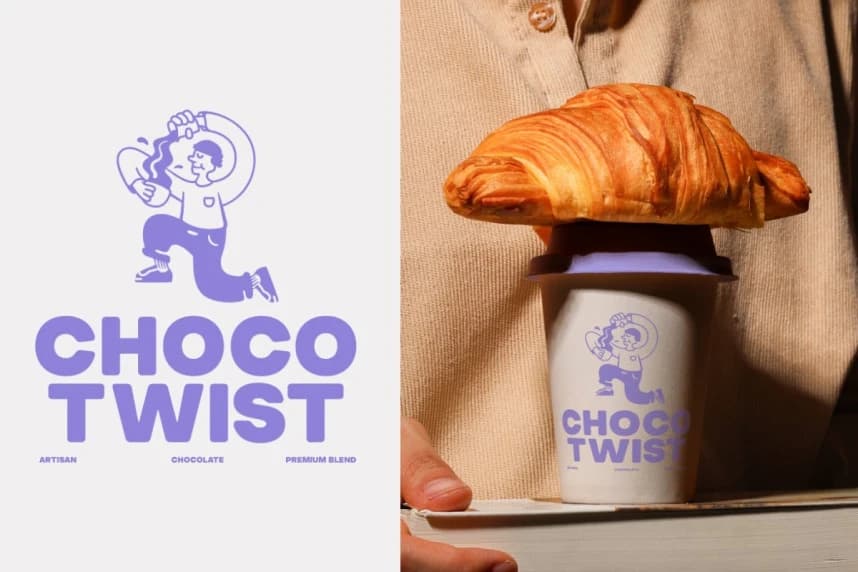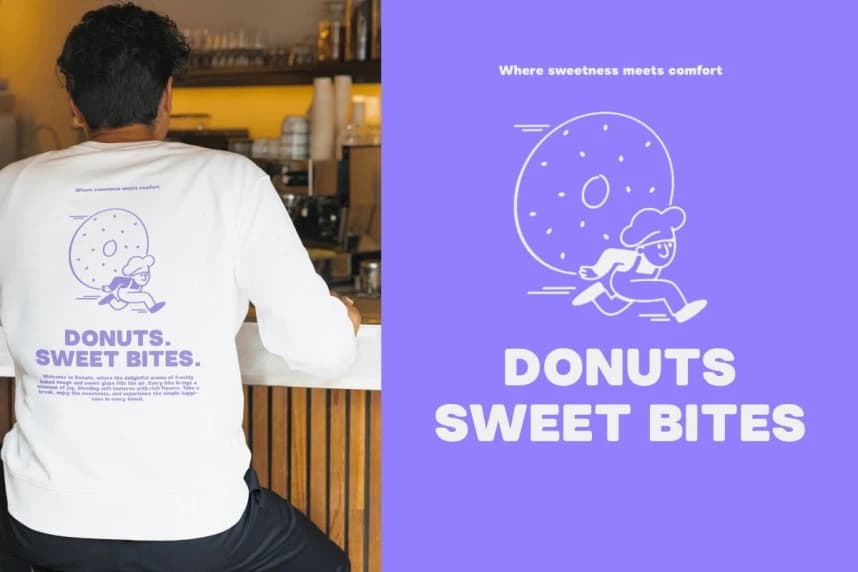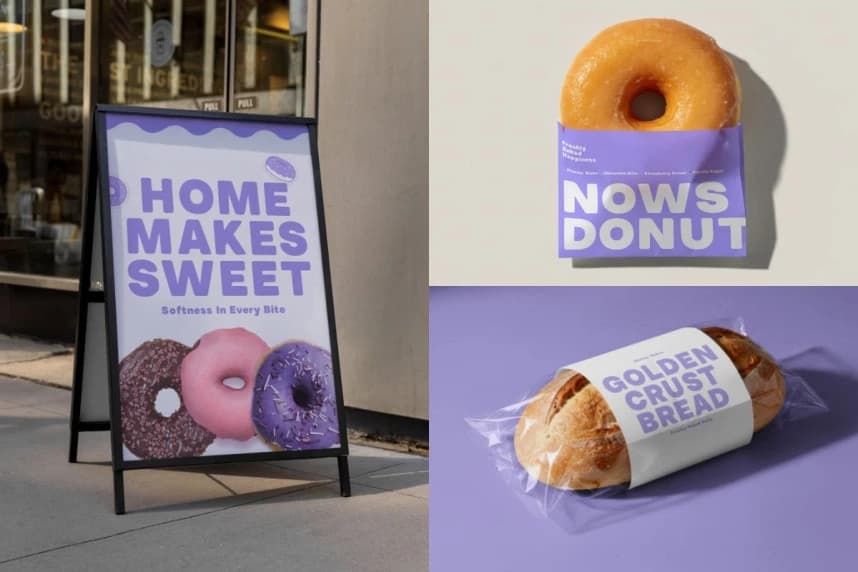
TBJ Moder Font
TBJ Moder Font, cesur ve modern bir görsel kimlik sunmayı amaçlayan çağdaş, yuvarlak hatlı bir gösteri yazı tipidir. Pürüzsüz eğriler ve temiz yuvarlak köşelerle tasarlanmıştır. Bu yazı tipi, büyük başlıklar ve modern markalaşmada öne çıkan dostça ama güçlü bir karakter sunar.
TBJ Moder Font, cesur ve modern bir görsel kimlik sunmak için tasarlanmış çağdaş, yuvarlak bir gösteri yazı tipidir. Akıcı eğriler ve temiz yuvarlak köşelerle üretilmiş olan bu yazı tipi, büyük başlıklar ve modern marka kimliğinde öne çıkan dostça ama güçlü bir karakter sunar.